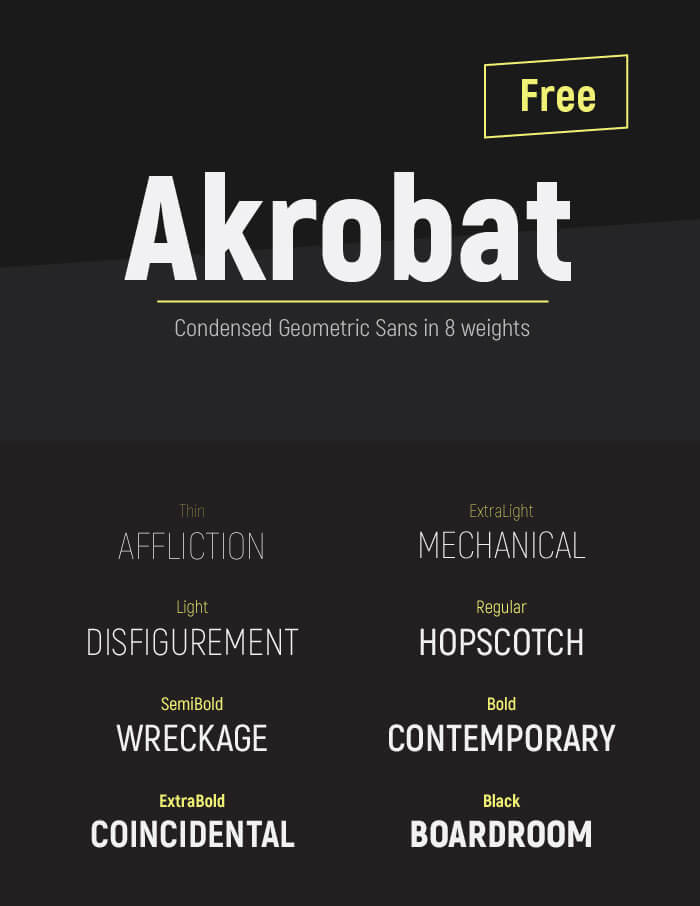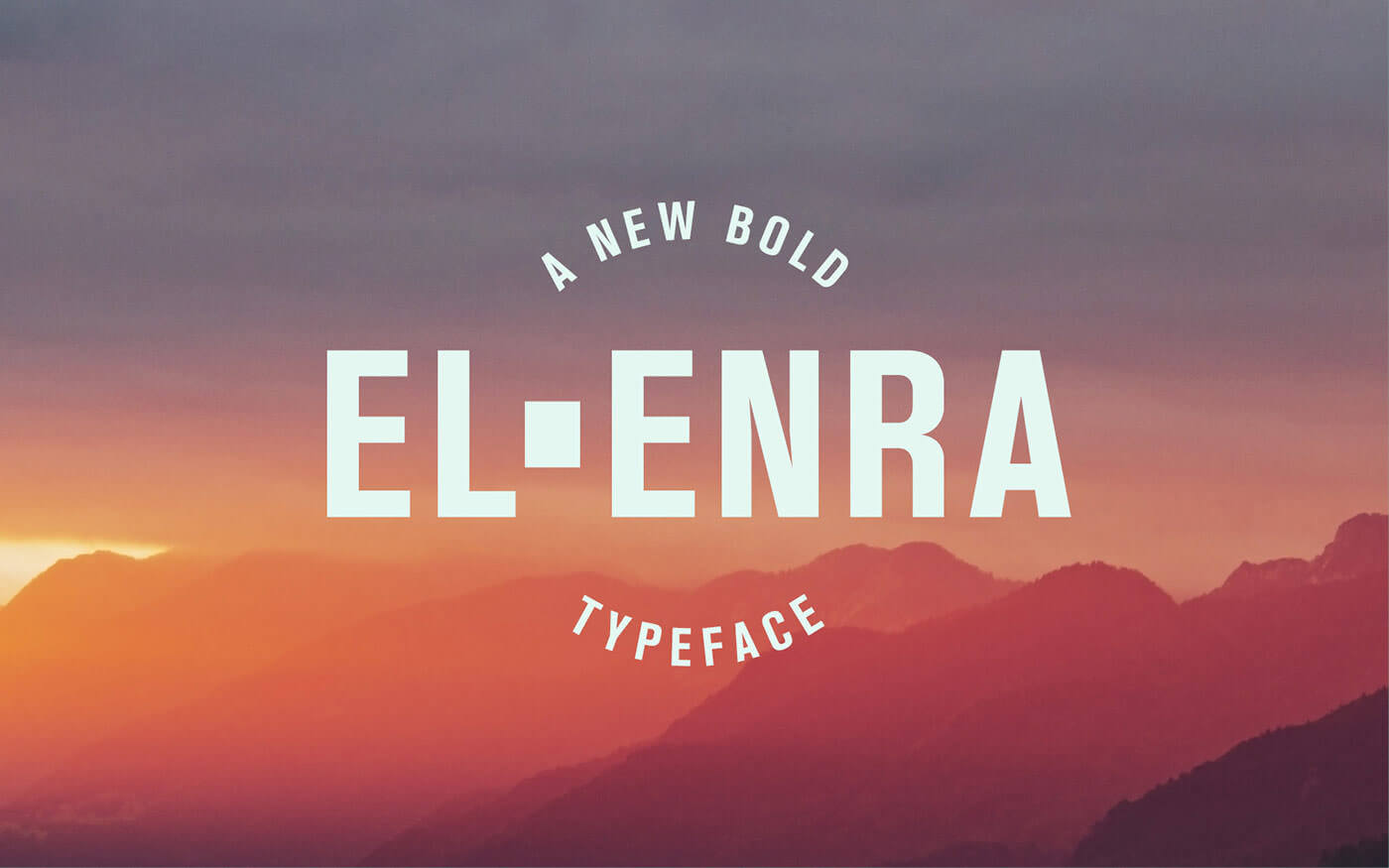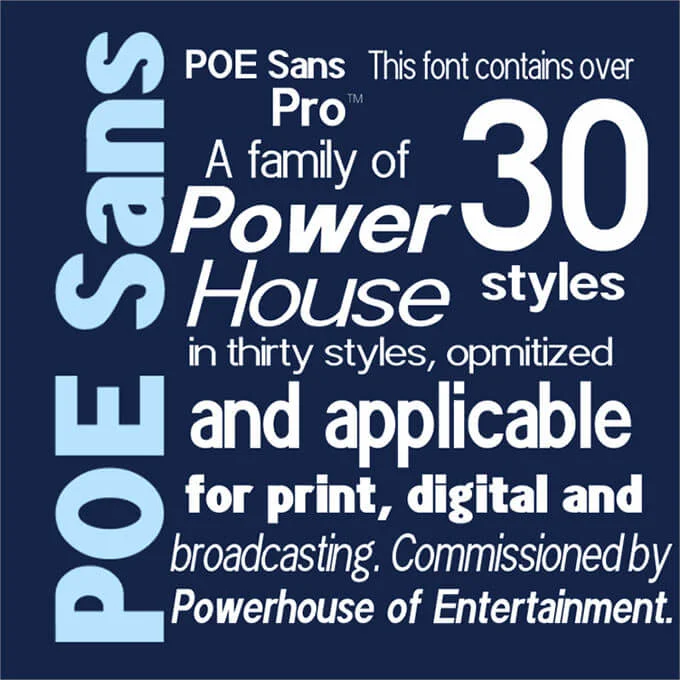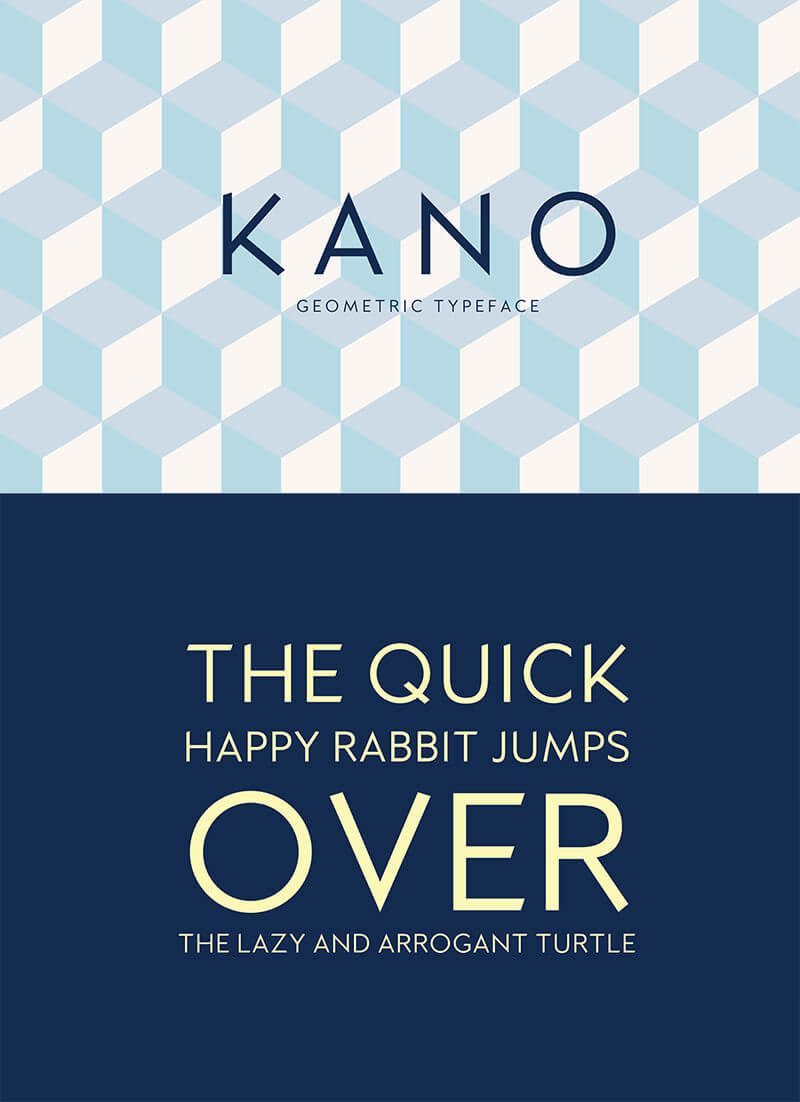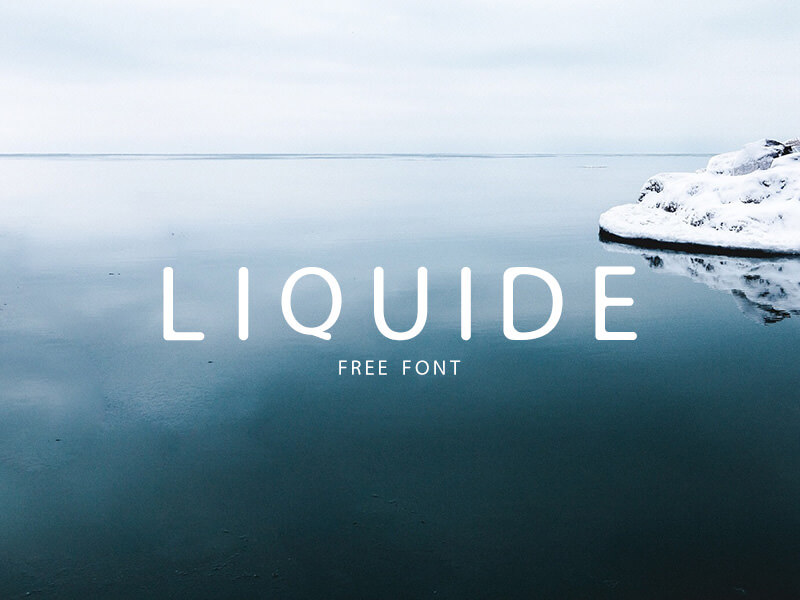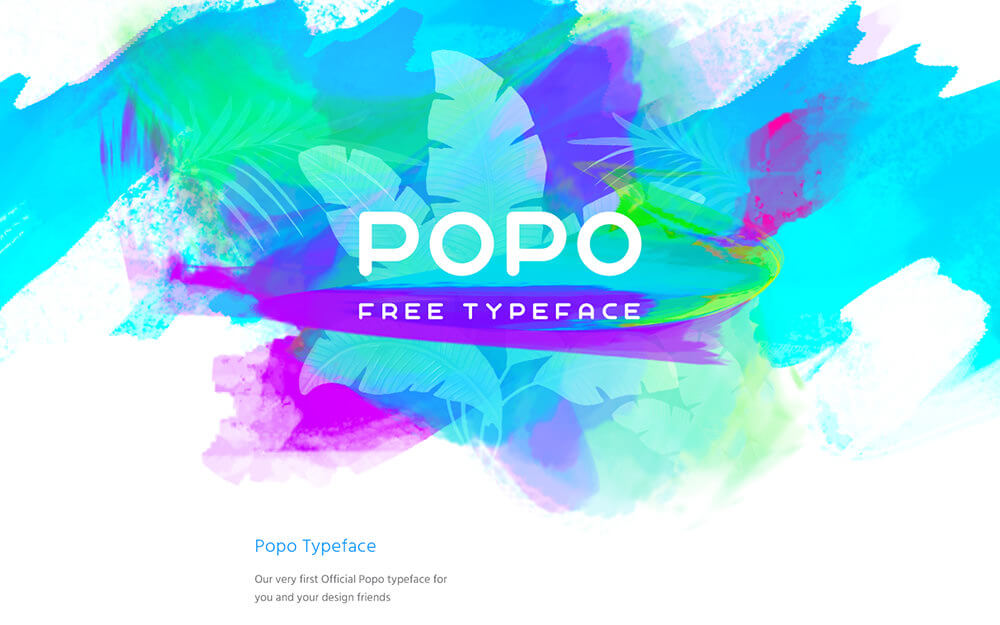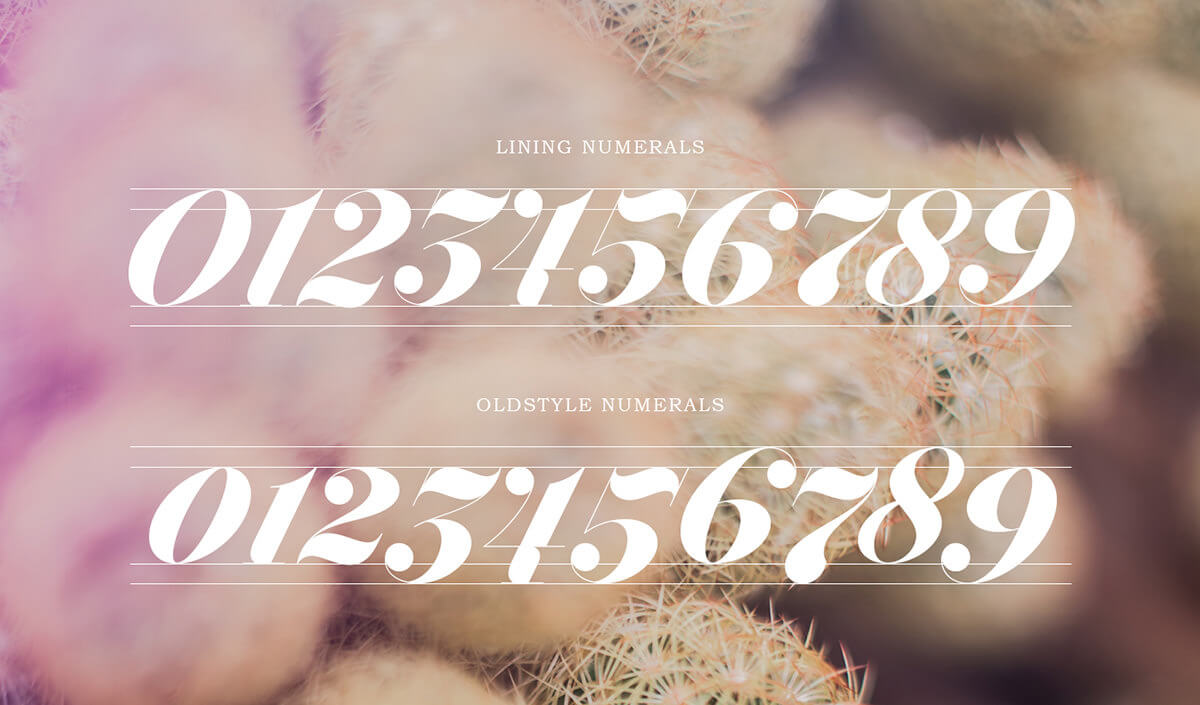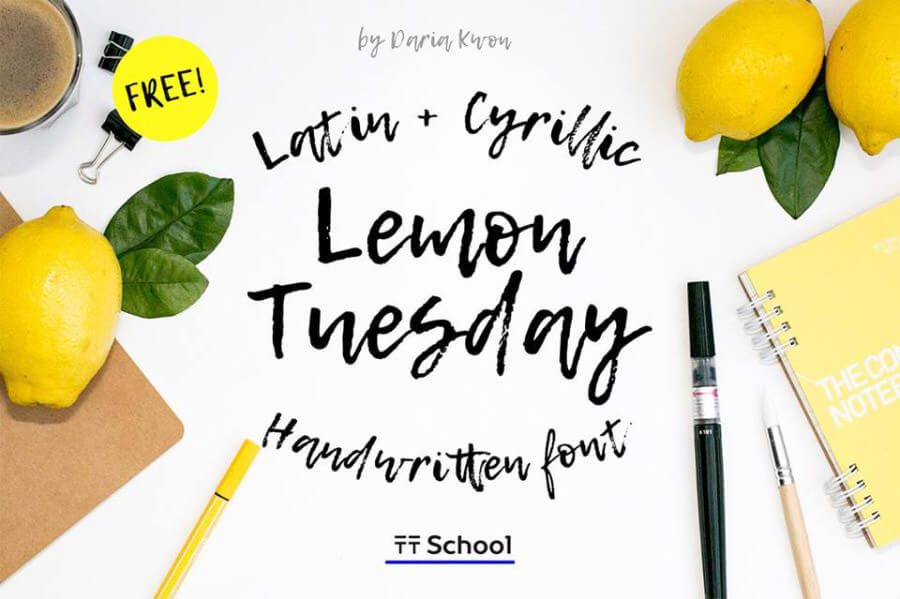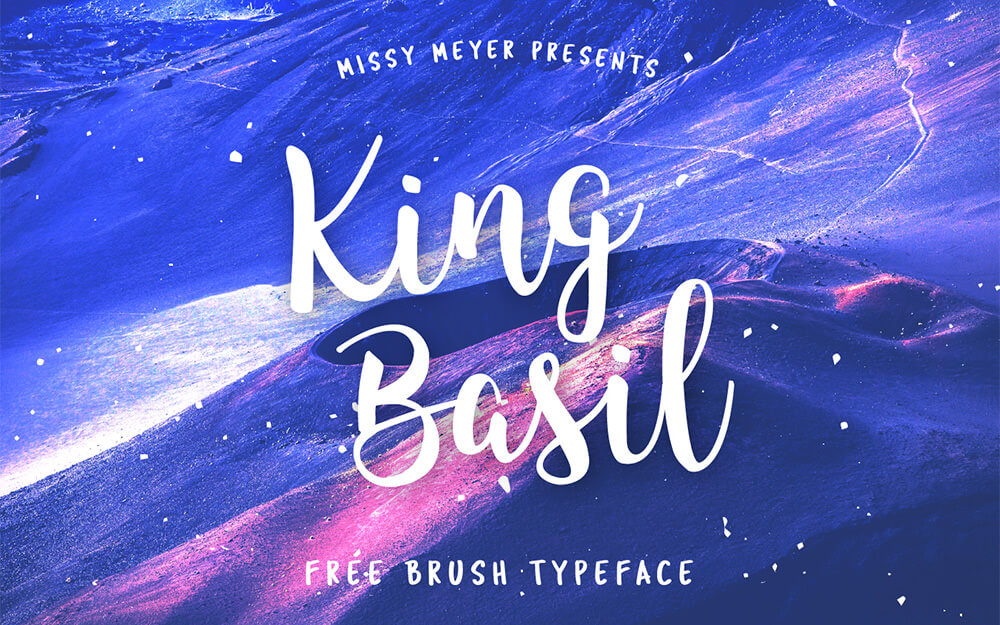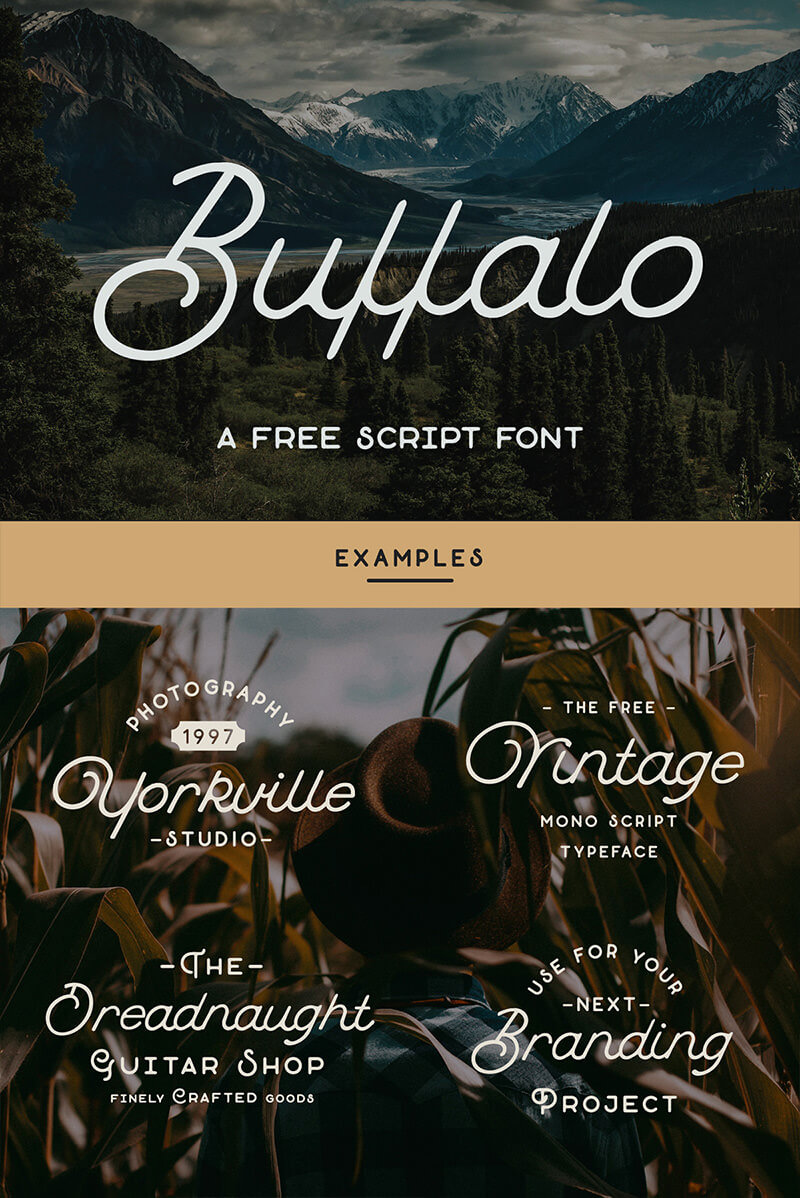
2016年,今年也有許多免費字體公開,光是在網路上就有超過600種,幾乎到了難以選擇的程度了。這回,將從2016年公開的素材當中,精選可以商用、並能免費下載的字體,分類歸納給大家。
為了完全展示畫面的可讀性,而精心設計出的字體,連網頁字體也都有收錄。
Mozilla OS 專用的字體組合,擁有 16 種不同粗細字級,更收錄超過 2600 種的符號。
具備 16 種類型的字體粗細變化,是一款只要稍作組合,就能擁有設計感的萬能字體。
在稍微纖長的風格中,提供 8 種類型的字體樣式,可以隨性使用的超群字體。
備齊 4 種不同的字體粗細樣式,相當講究閱讀性,是只要擁有就會相當方便的萬能字體。
這款字型的圓角設計、給人溫柔親切感。
偏圓的字體,依粗細不同,收錄兩種字級樣式。
收錄了 18 種粗細不同的風格,隨意組合便可以輕鬆創造設計感。
能夠因應所有設計,從極細到極粗字體,總計收錄了9種字型樣式。
去除粗體字的稜角,是一款既親民又別具效果的字體。
不論什麼設計都很適合的簡約風格,因應字體粗細程度,收錄了三種不同的粗細樣式。
粗體字也能夠順利閱讀,是適用於標題及文案的字體。
稜角感的粗體字風格,使用在標題、文案、logo、及海報等都非常適合。
超過 30 種以上不同的字體樣式,商用也 OK、是可以隨意使用的無襯線免費字體。
簡單又別具現代風格的細款字體,用在任何設計上都容易搭配,相當方便。
怎樣的設計都好搭,用粗體字抓住流行趨勢,展現幾何圖形般的復古風格。
受超人氣字體 Futura 和 Avenir鼓舞,這款是看起來非常舒服、可以廣泛運用的字體。
因為圓潤的邊緣設計,可以擁有柔和又容易親近的印象。
微微圓角的邊緣設計,展現溫柔又友好的印象。Seme Bold 風格可以免費下載。
不選很簡單的設計也沒關係,這款字體是怎樣的作品都能使用的萬能字體。
圓滾滾的樣式展現溫和友善的印象。
稍微的稜角風格讓人印象深刻,是連粗體樣式都相當豐富的字體。
更新後更方便使用的免費字體。
有如深海般的神秘美感,最小字體也相當好用的字體。
重視清楚鮮明的閱讀感、是款極簡的無襯線字體。可以免費下載 Light 版本。
因應想組合使用的時機,備齊了 6 種不同粗體樣示,連商用專案都可支援。
襯線體字型
連斜體樣式都很華麗、設計感超群的襯線體字型。
簡單又好用的免費字體,連網頁字體也可以支援。
齊備的 16 種字級,正經路線的免費字體,也是一款只要擁有就相當方便的萬能字體。
備有 5 種不同字型字級,連阿拉伯文都完全適用。
近期才剛更新,是襯線體字型中,相當難得收錄 8 種風格的字體。
以古風字型為基底,表現出別有風味和諧氛圍,是一款傳統風格的字體。
有如手繪般自然,擁有不規則曲線的襯線字體。
完整還原 19 世紀時期的襯線字體,讓你在所有的設計製作上活躍。
古典美感強勁的襯線字體,是重視可讀性的選擇。
有 ZARA 質感,收錄 3 種復古風格的的免費字體組。
從極細到極粗風格,合計 16 種,非常好用的鋼板襯線體。
華麗大氣,注重可讀性的鋼板襯線體。
混合三種不同字體,去無存菁後的優秀鋼板襯線體。可以免費下載 Regular 和斜體樣式。
跟隨時尚潮流很簡單,現代感的襯線字體,是令人眼睛一亮的風格。
草書字體
稍微加粗的草書字體,適合想用展現華麗氣氛的時機。
有如塗鴉般,展現愉快氛圍的草書字體。
2016 年流行趨勢代表、筆刷風格的手寫款免費字體。光是使用就讓設計風格煥然一新。
Antre
繞圈纏繞、捲曲狀的風格是魅力所在,細字樣式的草寫風格。
細線描繪的手寫字型,不管哪一種專案都可以簡單搭配。
圓滑令人鍾愛是特色、一款展現經典風格的手寫字體。
演繹經典頹廢風尚的字體,特別的大字設計引人注目。
相當時尚的連體字也收錄,是設計感極高的手寫風字型。
殘留的手繪質感,更加展現手作風格的草書字體。
潦草亂塗般、卻意外好看的手寫字體。
舊款的老式草書,運用在 logo、廣告 Banner 等也很適合。
自然感的手繪筆刷字體,可以同時組合草寫體與細長款大字母。
充滿時尚感的美麗草書藝術體。
可以運用在商業設計的筆刷草書。
手繪款的筆刷風格,用在 logo 或是標題或許也是個好選擇。
光是輸入文字就被時髦的 logo 風給吸引,充滿躍動感的手寫款筆刷字體。
融合紐約咖啡廳的美式藝術風格,粗體樣式的自然系手寫風格。
以舊款手寫文字作為樣式的字型,放大尺寸也可以很顯眼的字體。
擁有溫柔氛圍的手寫感,看起來相當自然的手寫字體。
用筆刷繪出來的粗體手寫體,展現滑稽的幽默樂趣。
The Beautiful Marjei Display Font
粗筆刷描繪出的自然質感,是相當令人喜悅的字體。
字體設計師以父親的手寫筆跡作成、做出這款擁有自然感的字型。
特別結合手寫體與草書字型,搭配出手繪風格。
細體字的手寫字體,追求「連用在電影銀幕都很漂亮」的程度。
第 1 彈起,變得稍微細長、逆勢回歸的字體,目前收錄了Regular 和 Bold 兩款樣式。
是怎樣的設計都合用的手繪風格,也有相當豐富的選擇,如連體字、顏文字等。
收錄了 4 種不同的字級,是稍稍偏圓的筆刷字體。
全部都是大字的非襯線字體,不整齊的線條呈現手作感。
各式設計都可以活用的展示用字體,用在品牌行銷等設計、做成 logo 等,都完全 OK。
缺角的英文字母設計,是相當特殊的細字免費字體。
在字型的邊緣維持圓角,是一款給人溫柔感的雕版字體。
這款免費字體,特色是用雙線描繪的雕版風格。
用細雙線描繪而成、並在字型的一部分加入裝飾。
看起來很有復古風的字體,Regular 風格中加入質感,Distressed 風格等也有 3 種類型可選。
用點點交結而成的英文字母,呈現既簡單又有設計感的風格。
Flower Display Serif Free Typeface
以花朵作搭配的襯線字體,是具有高級感的可愛風格。
用鉛筆畫草圖般、可以做出像全面塗鴉般的字體。
因為原先是要付費的字體而相當重視品質,是一款展現出色「玩耍」風格的字型。
重複堆疊的筆刷質感,呈現經典復古的風格,原創性相當高的襯線字體。
這款免費字體,可以展現有如用粗麥克筆來書寫般的質感。
在粗糙筆刷感上、再添補加粗的無襯線字體,非常好用,又相當有設計感。
從日文郵戳意識出來的英文字體,Light 和 Regular 兩種風格都有收錄。
雖是古樸感的字形,卻給人一種冷酷感。由於擁有 5 種字級,是讓設計也變得很簡單的萬能款。
漢字是怎麼寫成的呢?一款能夠看見字型起源的古文風格字體。
讓漫畫裡的襯線體也變好用的免費字體。字體設計相當重視細節。
據說這款字體,是模仿自「泡泡、泡泡!」的漫才demo 中、在角色名稱上用到的字型。
參考森川龍文堂假名活字版的片假名作成的文字。特點是收錄的字體相當豐富、約有 3200 字,包含漢字及符號。
圓粗體的樣式洋溢出懷舊感,相當上手的字體。收錄 3 種字級。